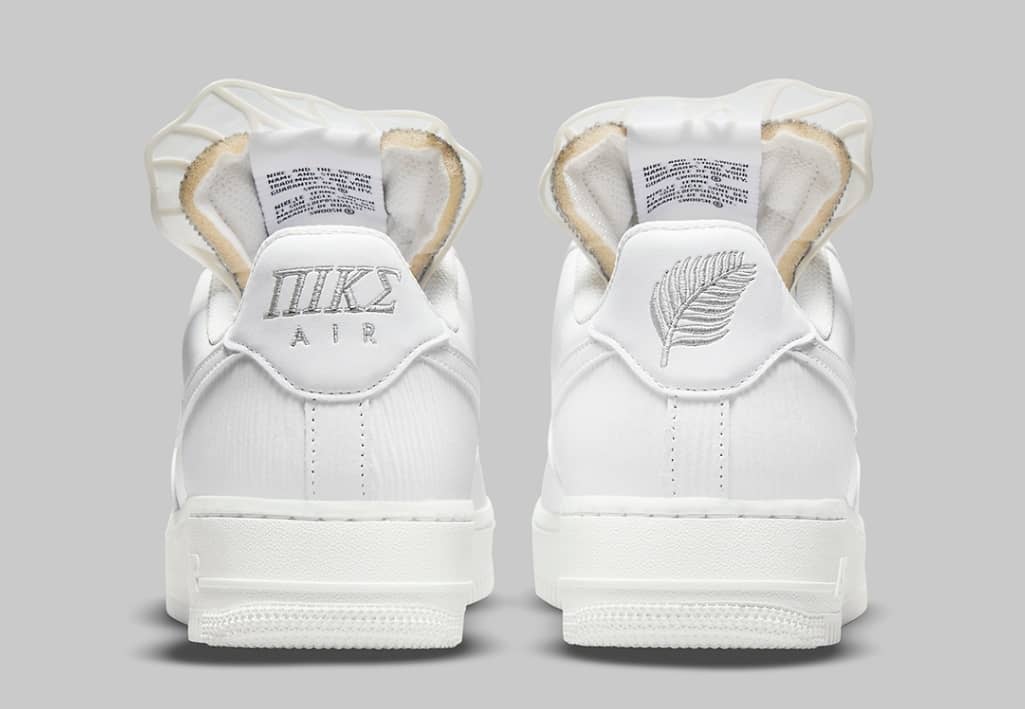
Nike rediseña su logo inspirado en la cultura griega y la audiencia no perdona el error en su tipografía
La firma pretendía enaltecer uno de sus renovados tenis y los resultados fueron todo lo contrario. Entra aquí para saber de qué se trata.
A propósito de la innovación en el modelo de zapatos Air Force 1 Low, Nike decide cambiar su logo, inspirado en la cultura griega y aunque pareciera no tener mayor diferencia con los tipos de tenis anteriores en esta línea lo único que no pasa desapercibido fue el error en su tipografía.
La marca quiso emular las letras del alfabeto griego por su similitud con las del alfabeto americano para la transcripción de su nombre ¡Gran error! ya que por mucho parecido que pudiera tener, emiten sonidos diferentes, algo que cambia completamente su lectura, así lo dejó saber Zoe Gardner experta en el tema desde su cuenta de twitter..
Esta usuaria de twitter fue la primera en detectar la equivocación cometida por la marca en un post a través de esta red social, en donde sin dudar procede a explicar que la letra “П” traducida al inglés corresponde a una “P” y de la misma forma la tipología “Σ” equivale a una “S” por lo que al traducirlo se lee “Piks” en lugar de “Nike”.
Como era de esperarse las críticas provenientes de usuarios en distintas redes sociales no se hicieron demorar, manifestando el desagrado por lo que pudo haber sido una falta de estudio y cuidado por parte de Nike siendo catalogado inclusive como una ofensa para la cultura griega.
El cambio en la tipografía y en los logos de las marcas es una estrategia crucial que ha funcionado en el marketing para tener éxito en el mercado, siempre y cuando sea estudiado el campo correctamente, de lo contrario en lugar de inspiración se puede terminar en ofensas.